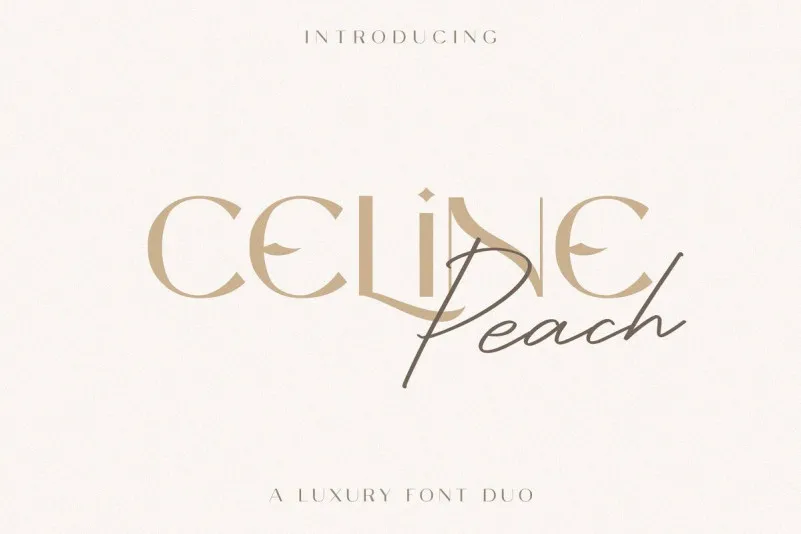
A Celine Peach Font Duo é uma paleta de duas fonts que oferece um toque sofisticado com a modernidade na ponta dos dedos. Ela se assemelha a um estilo de sans-serif elegante e tradicional, mas com uma pitada de revolução moderna que encaixa perfeitamente com a escrita detalhadamente realista em script retrabalhado, criando um contraponto vibrante e encantador. A Celine Peach – uma paleta sofisticada de fontes – se tornará o queridinho para marcas de moda, blogs tendências, boutiques de casamento ou qualquer negócio que deseja soar ao mesmo tempo elegante e estiloso.